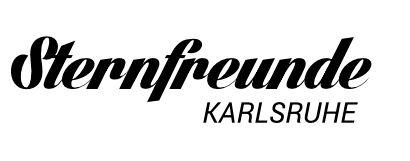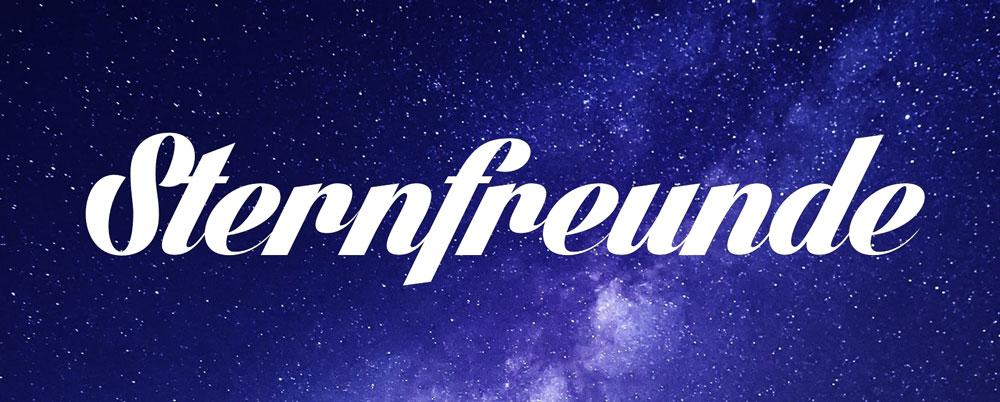
Lighthouse Personal Use - Alternative gesucht
ich suche eine kostenlose Alternative zur "Lighthouse Personal Use", oder andere Vorschläge.
Der Name ist nicht kreativ, aber so abgestimmt. :-P "Sternfreunde Karlsruhe", wobei nur Sternfreunde eine "besondere Schrift haben soll. Der Stadtname kommt dann dezent darunter. Ich habe jetzt schon zich Schriften angeschaut und finde die "Lighthouse Personal Use" eigentlich nicht schlecht.
Ich denke etwas "Freundliches" mit Schwung, oder was sagen die Profis?
Nee, die bringe ich gar nicht mit dem Thema zusammen.
Die Schrift vermittelt auf alle Fälle keine "trockene, langweilig-ernsthafte" Wissenschaft, sondern eher eine freudige Neugier und einen angenehmen Zeitvertreib.
Ich finde die Lighthouse dafür auch ganz nett – allerdings würde ich für Karlsruhe keine Kursive verwenden. Die unterschiedlichen Neigungen der beiden Schriften machen mich kirre.
Die "Karlsruhe" Schriftart war nur Platzhalter. Ich dachte da an etwas ganz schlichtes ohne Ablenkung, Kursiv ist wirklich doof! :-)  Nochmal danke!